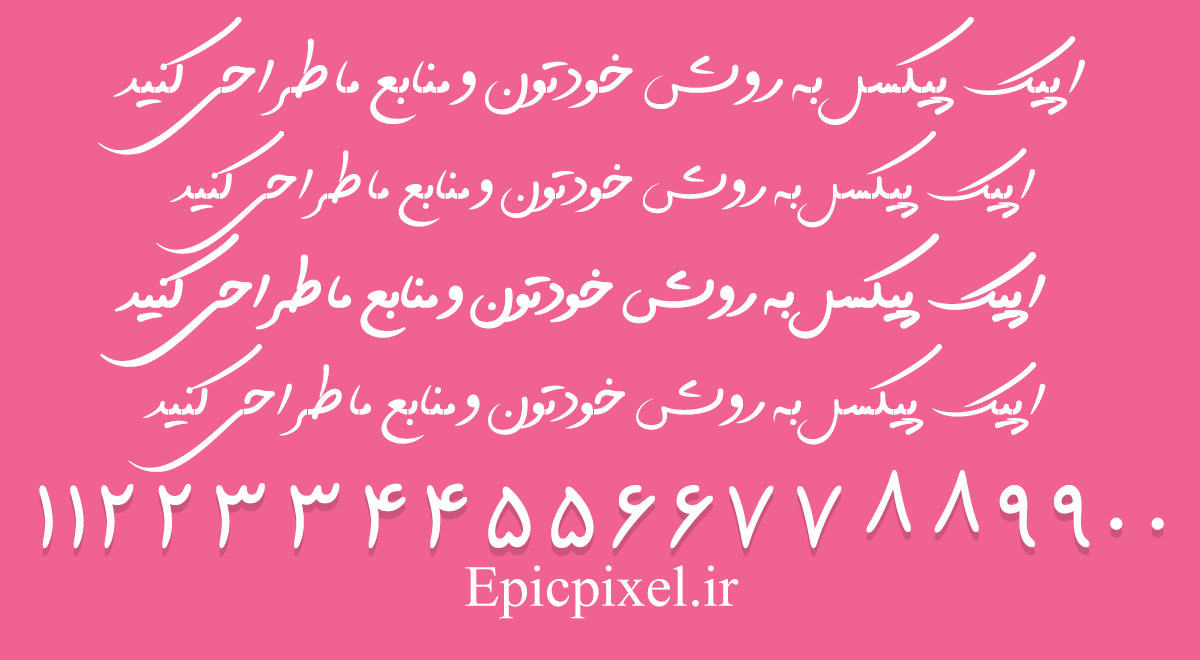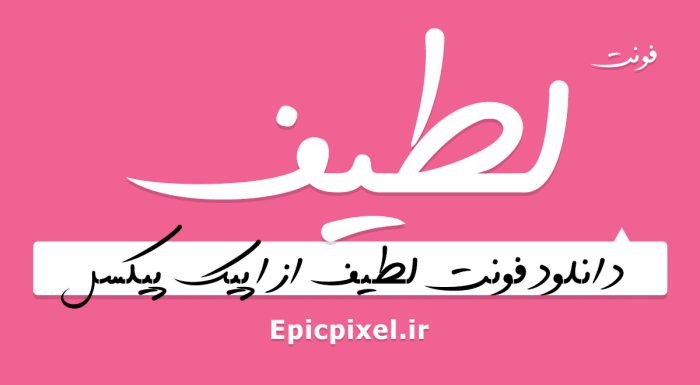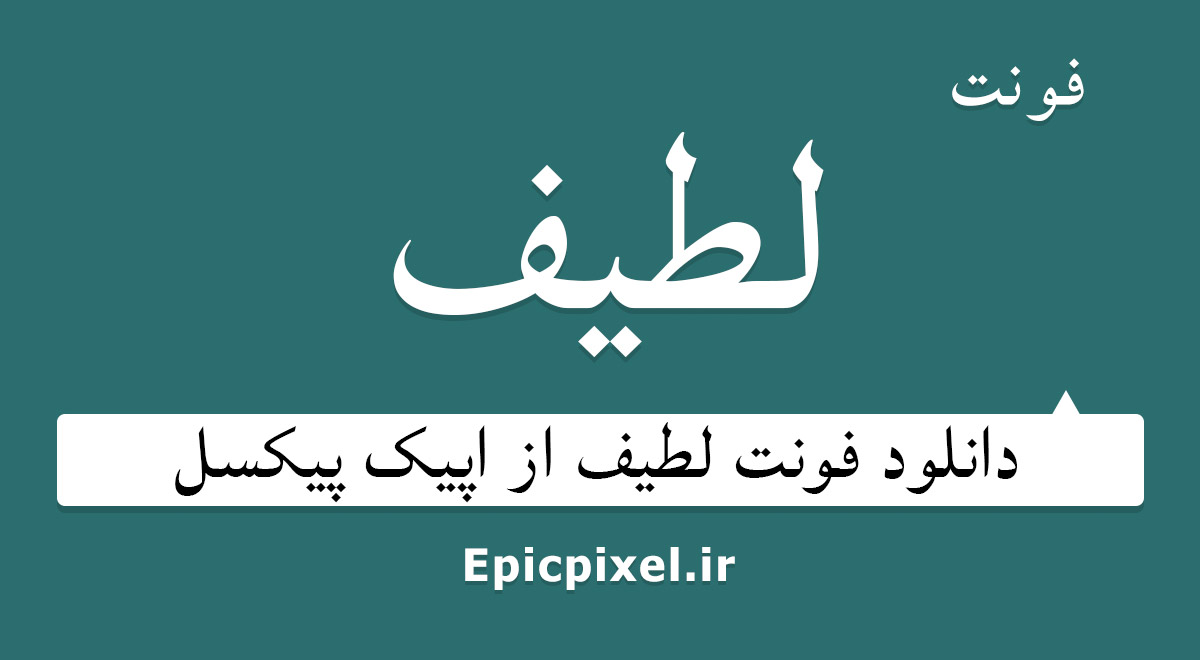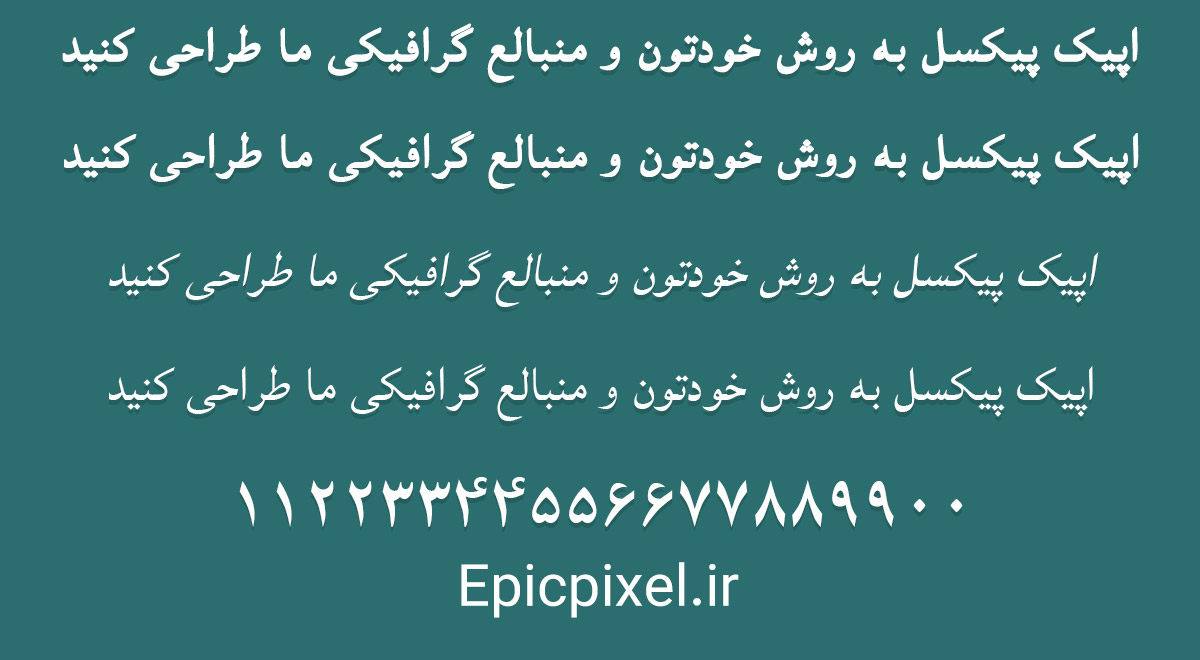
2 فونت لطیف فارسی
دانلود مجموعه کامل فونت Latif فارسی Font لطیف رایگان |
| ⭐ مجموعه فونت | دانلود فونت دیما لطیف رگولار Font Dima Latif regular فونت فارسی لطیف Font Lateef |
فونت لطیف یه فونت خیلی قشنگ و خاص برای کارای گرافیکیفونت لطیف یه فونت فارسیه که خصوصیات خاصی داره ، این خصوصیات باعث میشه از بقیه فونتها متفاوت باشه. تو این مقاله میخوایم بهتون بگیم چه چیزایی تو این فونت هست و چه جوری میشه ازش استفاده کرد.
ویژگیهای فونت لطیفاین فونت رو بر اساس قلم نستعلیق ساختن که یکی از قلمهای خوشگل و پرکاربرد تو خط ایرانیه. چجور فونت لطیف رو دانلود و نصب کنیم؟بعد از دانلود فایل فشرده که فونت لطیف توش هست، از حالت فشرده دربیارید و فایلهای TTF یا OTF رو تو پوشه Fonts سیستم عامل خود کپی کنید. بعد میتونید تو نرم افزارهای مختلف از فونت لطیف استفاده کنید.